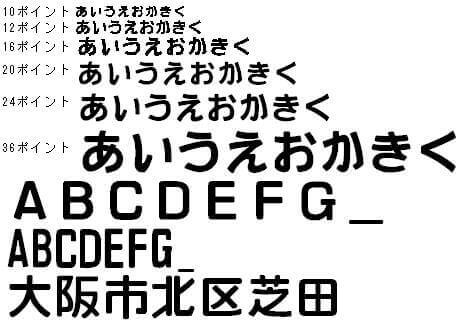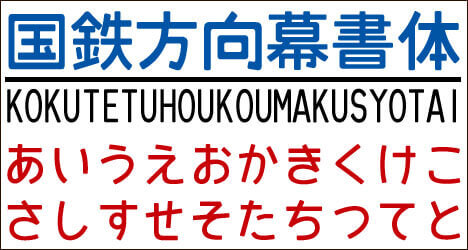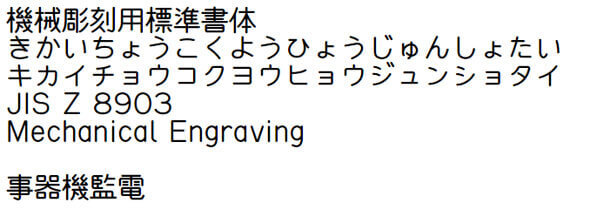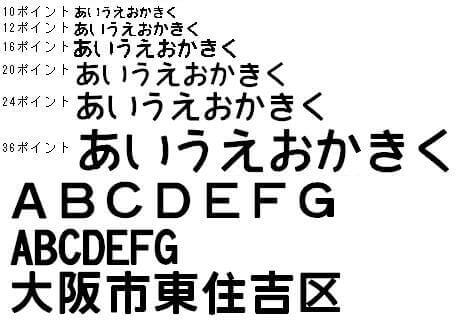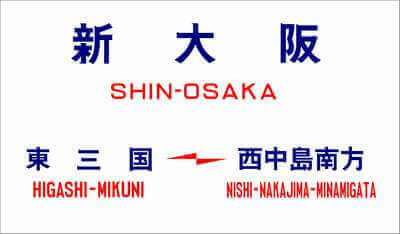
無料でダウンロードできる国鉄フォント集
懐かしさを感じる国鉄時代に使われた書体を集めてみました。国鉄の駅名標などを再現したものもあり国鉄ファンなら見逃せないフォント集になっています。フォントとしても見やすい書体になっており、見やすいフォントを探している方にもオススメです。
コマルひげ文字フォント
かつて大阪市交通局が路面電車や地下鉄の案内表記に使っていたフォント。手書き風の文字にヒゲがついた独特のデザインになっています。
機械彫刻用標準書体
工業的な彫刻によって文字を作製するときの標準として日本工業規格(JIS)に定められた書体。
国鉄っぽいフォント
国鉄当時、駅の案内表示などに使われていた各種案内表示のピクトグラムを搭載したフォント。
国鉄方向幕書体
国鉄のころの車両の方向幕の独自書体を再現したフォント。
手書き風書体(国鉄フォント)
建植式の駅名標で、北海道から中国地方にかけて、ある程度統一して使われていたフォント。